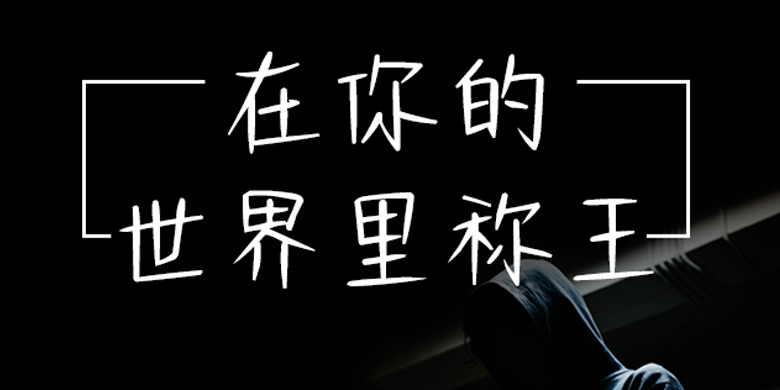
品牌:方正手迹设计师:宋昱东发行时间:2020字库编码:简繁扩展(GBK)分类:常规书写·硬笔字体属性:精品字
在你的世界里称王是一款风格独特的手写体。该字体笔画平直尖锐,少有曲线,原本有的曲线大部分用直线代替,这样体现出字体的速度力量感。适用于文艺类书刊、品牌广告和产品包装设计,以及社交网络的个性化用字。